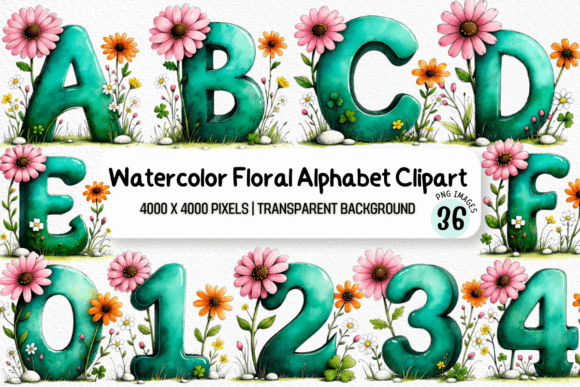
Whimsical Flower Alphabet Clipart Bundle
Si vous recherchez des ressources de haute qualité comme Whimsical Flower Alphabet Clipart Bundle, ce pack premium est un choix fantastique pour vos projets créatifs.
Conçu avec précision, Whimsical Flower Alphabet Clipart Bundle offre des vecteurs nets, une typographie fluide et une licence commerciale pour une tranquillité d'esprit.
Que vous créiez des produits POD (impression à la demande), des invitations de mariage ou des visuels pour les réseaux sociaux, Whimsical Flower Alphabet Clipart Bundle est un choix idéal.